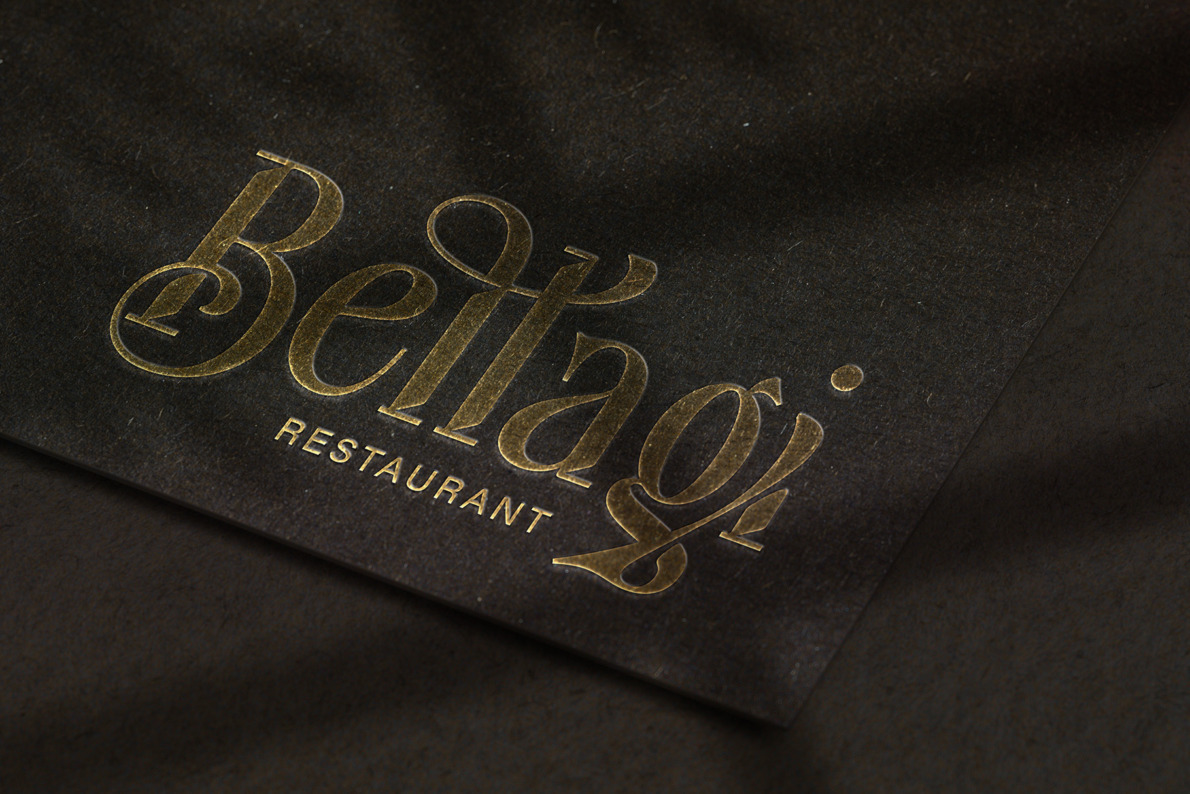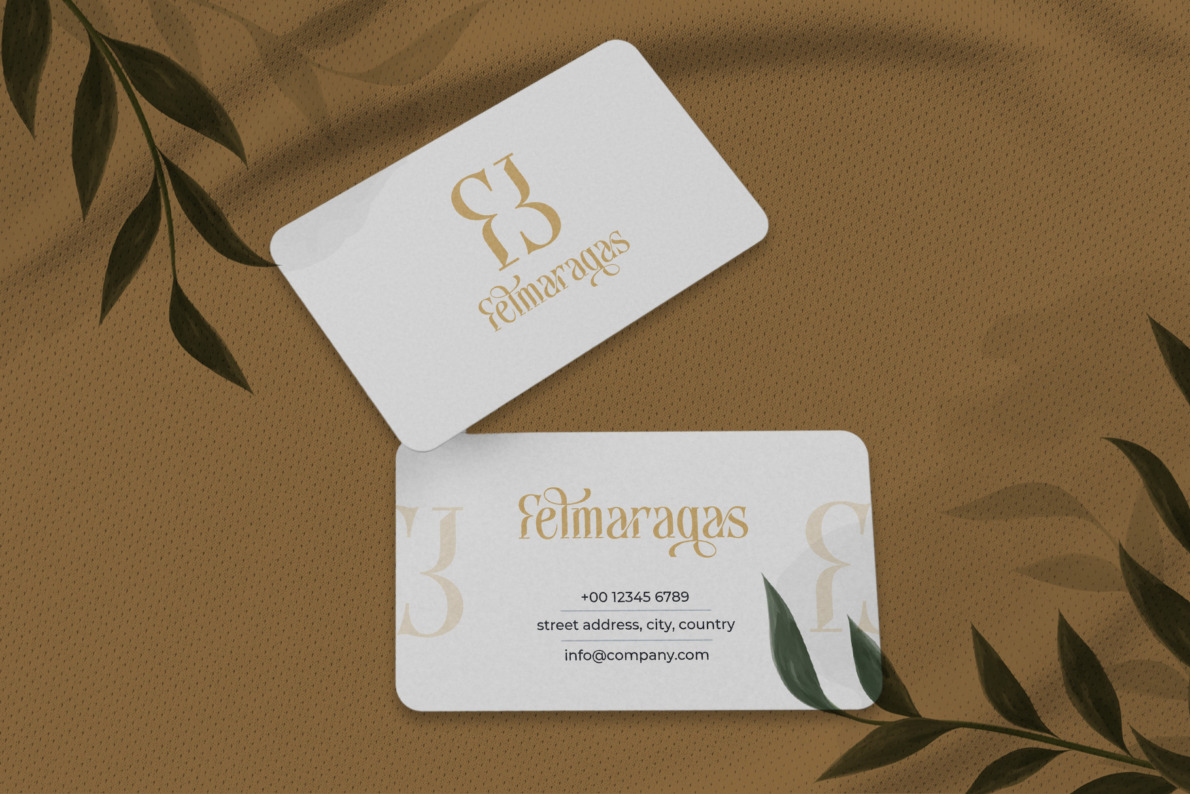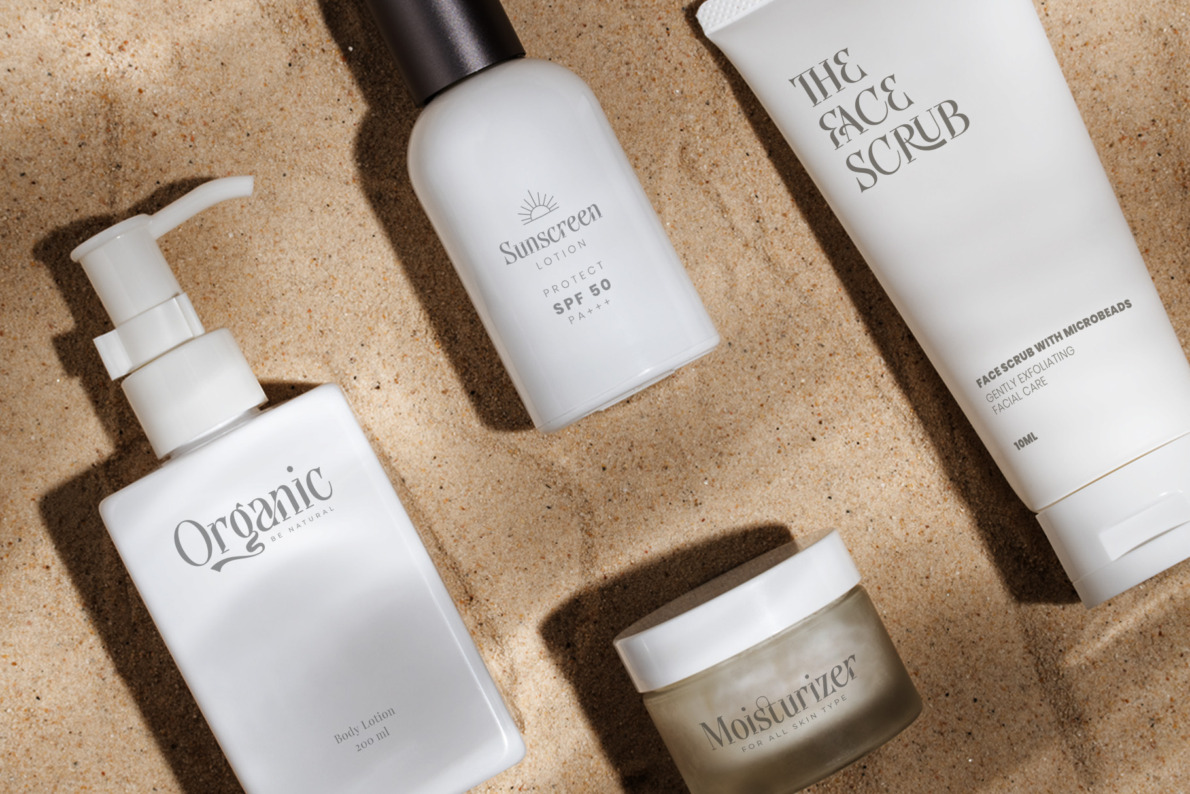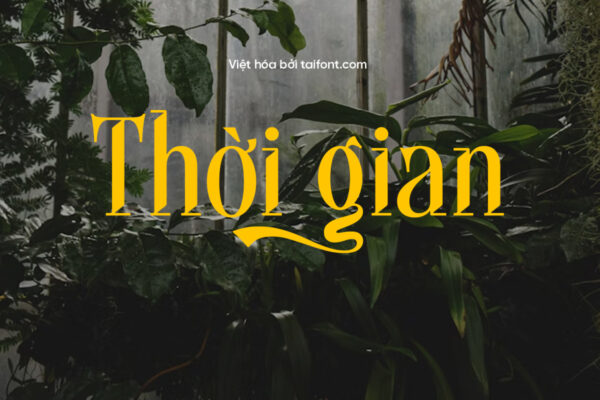
Giới thiệu về Font TF Sabiant Việt hóa
TF Sabiant Việt hóa là một font chữ có chân (serif) nổi bật với vẻ đẹp sang trọng, tinh tế và đầy cuốn hút. Font này được thiết kế với những đường nét thanh lịch, mềm mại nhưng vẫn giữ được sự rõ ràng và chuyên nghiệp, toát lên phong thái quý phái và đẳng cấp, lý tưởng để tạo nên sự độc đáo cho mọi thiết kế.
Với sự tinh xảo trong từng ký tự và tính thẩm mỹ vượt trội, Sabiant là lựa chọn hoàn hảo cho các ấn phẩm cần sự sang trọng và khác biệt, đặc biệt là trong các lĩnh vực:
- Thiết kế mỹ phẩm: Hoàn hảo để sử dụng trên bao bì sản phẩm, nhãn chai, hoặc các chiến dịch quảng bá mỹ phẩm. Font này giúp khẳng định chất lượng, sự sang trọng và vẻ đẹp tinh túy của sản phẩm, thu hút ánh nhìn của khách hàng và truyền tải thông điệp về sự quyến rũ, đẳng cấp.
- Thiết kế thời trang: Lý tưởng cho các thương hiệu thời trang cao cấp, từ logo, nhãn mác sản phẩm, lookbook, đến các chiến dịch quảng bá bộ sưu tập. Font này giúp truyền tải vẻ đẹp thanh lịch, đẳng cấp và độc đáo của trang phục, nâng tầm giá trị thương hiệu.
- Thiết kế tạp chí: Phù hợp để sử dụng cho các tiêu đề chính, lời dẫn, hoặc nội dung bài viết trong các tạp chí về thời trang, làm đẹp, hoặc phong cách sống. Nét chữ có chân của Sabiant giúp tăng tính trang trọng và dễ đọc, đồng thời tạo cảm giác cao cấp, thu hút độc giả.
- Thiết kế nhận diện thương hiệu: Lý tưởng cho các logo, tagline hoặc bộ nhận diện thương hiệu muốn truyền tải sự tinh tế, uy tín và sự thanh lịch. Sabiant giúp xây dựng một hình ảnh thương hiệu vững chắc và dễ nhận diện.
Với TF Sabiant Việt hóa, bạn có thể dễ dàng thổi hồn tinh tế, sang trọng và vẻ đẹp hoàn hảo vào các thiết kế, tạo ra những sản phẩm không chỉ đẹp mắt mà còn đầy cảm xúc và sức hút đặc biệt.
Font Việt hóa TF Sabiant – Nhiều glyphs